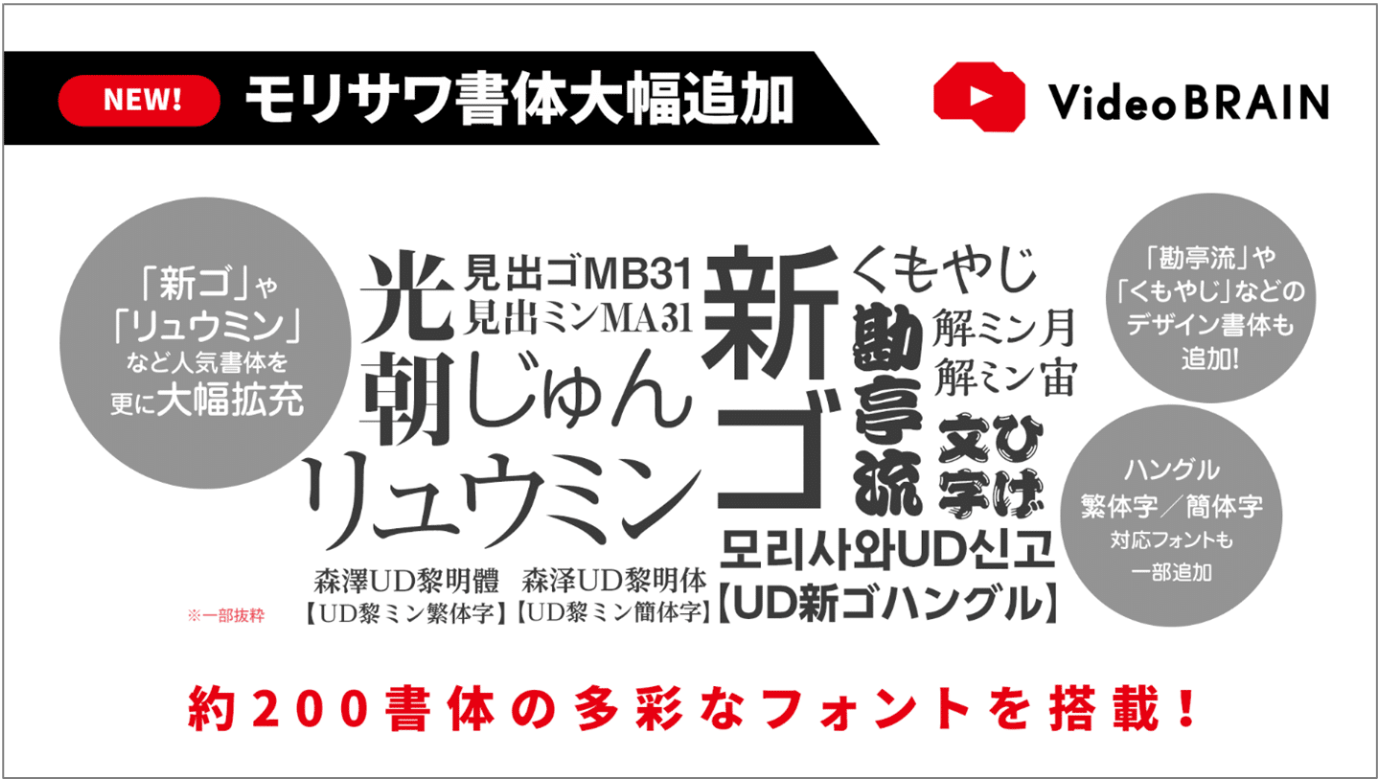
ビジネス動画の内製化を加速させた「Video BRAIN」
信頼感の高いフォントが
アウトプットの質を向上
独自のAI技術を活用した動画編集クラウドサービス「Video BRAIN」を核に、SNSの配信分析ツール「Insight BRAIN」、動画自動生成サービス「V-matic」などの各種サービスを提供する、株式会社オープンエイト(以下、オープンエイト)。Video BRAINには、モリサワフォントの197書体が搭載されている。変化のスピードが著しい動画編集領域で高い支持を集め続ける理由や、Webフォント導入の決め手などを、顧客担当の佐伯氏、開発担当の古山氏に伺った。
「誰でも簡単に」が変えた、オンラインコミュニケーション時代のビジネスの形
DX化への取り組みが進む近年、ビジネスシーンにおいて動画コンテンツの活用が盛んに行われている。SNSへの投稿や自社商品・サービスの紹介といった対外的なものから、人事採用、社内広報や作業マニュアルなどその用途も広い。
戦略的に動画を活用しようとするときに、課題となるのがコストや制作のスピード感だ。従来、専門的なスキルを必要とする動画制作は外部へ委託するケースが多く、内製化のハードルは高かった。そこでオープンエイトは、Web ブラウザ上で動作する「誰でも簡単に使える」動画編集ツールの開発に着手。独自のAI技術を活用して、PowerPointのように直感的に操作できるクラウド型動画編集ツール「Video BRAIN」を2019年に公開した。
以降も、新機能追加などの定期的なアップデート、素材やテンプレートの拡充を重ねて使いやすさを追求するとともに、既存顧客に動画活用のサポートや提案を行ってきた。こうしたユーザーに寄り添うサービスが支持を広げ、Video BRAINはオープンエイトのコア事業に成長。現在は600を超える企業・自治体に採用されている。
コロナ禍で直接的な対面が難しくなったこの数年は、社内外のコミュニケーションツールとしての動画ニーズも急伸している。新入社員の紹介動画などはその一例だ。
「文字情報だけで人となりを伝えるのは難しいですし、従業員向けの動画コンテンツがあれば、社歴が浅い方も会社のカルチャーをつかみやすいという利点があります」と、顧客の動画活用を提案・サポートする佐伯氏は話す。また、イベントなどの案内も静止画や動画を織り交ぜたリッチコンテンツとすることで、ユーザーの目に留まりやすくなる効果があるという。
オンライン・コミュニケーションが一般化する中で、動画は欠くことのできないビジネスツールとなった。その編集制作をVideo BRAINのサービスが支えている。
TypeSquareとサーバーフォントの併用でシームレスなデザイン体験を実現
Video BRAINは当初フォントの選択はクライアントOS・Webブラウザの標準フォントに依存していたが、現在では動画内の表示フォントに197書体のモリサワフォントをWebフォント、サーバーアプリフォントとして導入しテロップ(字幕)表示などで利用できる。
Video BRAINのプロダクトマネージャーとして新規機能の開発や改善、課題の分析に当たる古山氏は、「ビジネス動画として使っていただく以上、お客様のPC環境によって完成する動画に差分が生じるのはサービスとして成り立たないと判断しました。モリサワフォントはビジネスシーンで広く普及していて信頼感が高く、種類も豊富なので、導入に迷いはなかったです。成果物の質を上げて競合に差をつけたい、という狙いもありました」と経緯を振り返る。
また、それまで動画の書き出し後にしか確認できなかったプレビューも、Webフォントを導入することでリアルタイムプレビューが可能になり、編集効率が大幅に向上した。サーバーフォントとの併用によって、「シームレスなデザイン体験を提供できるようになった」(古山氏)という。
モリサワフォントを搭載したVideo BRAINでは、どのようなフォントが選ばれているのか。利用率の高いものを聞いた。
「ゴシックMB101とA1ゴシックです。動画内での視認性、判読性が高いフォントのためVideo BRAINに搭載しているテンプレートではこのフォントをデフォルトフォントとして採用しています。クライアントもフォント変更はせずに動画を作成するケースが多いのは、数秒でシーンが切り替わっていく動画でもはっきりと読み取れる、デザイン性の高さが評価されているからだと思います」と古山氏は話す。
Video BRAINテンプレートとして使われている「ゴシックMB101」
そのほかにも利用シーンに応じて約200種類のフォントを使用可能
BtoB(※1)のコミュニケーションにおいては、テロップの見やすさ、読みやすさが優先される傾向にあり、また、フォントに関する知見を持たないユーザーが、特段強いこだわりを示すこともなかった。しかし、そういった状況も変化のきざしを見せているという。
「営業用途で動画を使い始めたお客様が、マーケティングやミーティングなどにも用途を広げていく、というように、組織内で動画活用を水平展開していくケースが非常に増えており、それに応じてアウトプットも多様化しています。表現の領域をいかに広げられるかという点で、Video BRAINの自由度は突出して高く、そこもお客様に高く評価していただいていると感じています」(佐伯氏)。
画像や映像、BGM、アニメーションなどの動画素材を豊富に揃え、多彩な編集機能で動画を自由にカスタマイズできるのはVideo BRAINの強みだ。そして、そこにはフォントのバリエーションも含まれる。一方で『動画素材の組み合わせ方やシーンに合ったフォントをどう選べばよいかわからない』という顧客には、サポートの一環としてオープンエイトのクリエーティブチームがアウトプットのイメージに合った制作例を提示することもあるという。プロの伴走を得て、顧客の制作スキルも向上し、最近は用途に応じて意識的にフォントを使い分けるケースも増えてきている。
「マーケティング用途やSNSで発信する動画には比較的デザイン性の高いフォントが使われることが多い」と古山氏。用途に合ったフォントを選ぶことで、動画の訴求力は格段に上がる。「もっとバリエーションを充実させていきたい」(古山氏)と、拡充にも意欲を見せる。
多言語展開でさらなる価値を提供
顧客からの相談で最近増えつつあるのが、東南アジアなどの海外現地法人で働く従業員への情報発信に関するものだという。社内報などの社内広報コンテンツや業務マニュアルを動画化することによって、海外の従業員にもタイムリーに情報を届けられる一方、彼らが正しく情報を受け取れる言語を表示できるかという課題も生じる。
「多言語展開は重要なポイントだと捉えています。英語はもちろん、アジア圏の言語も網羅しておきたい。弊社の成長という点から考えても、グローバルがキーワードになってくるでしょうね」と佐伯氏は話す。
今後は多言語への対応とともに、フォントが持つ訴求力を生かした提案を推進していきたいという。
「合字(※2)が使えるようにする 、そしてモリサワフォントの美しさを存分に生かすためにも、カーニング(※3)ができるようにするといった、機能面も改善したいです」(古山氏)。「フォントと相性のいいテンプレートを提供しているのですが、さらに充実させていこうと計画しています。魅力的な動画が簡単に作れるよう、モリサワさんと我々の知見をかけ合わせて、新しい価値を生み出していけるといいなと思います」(佐伯氏)。
※2 合字…2つ以上の文字を組み合わせて1つの文字にしたもの
※3 カーニング…文字間のスペース調整